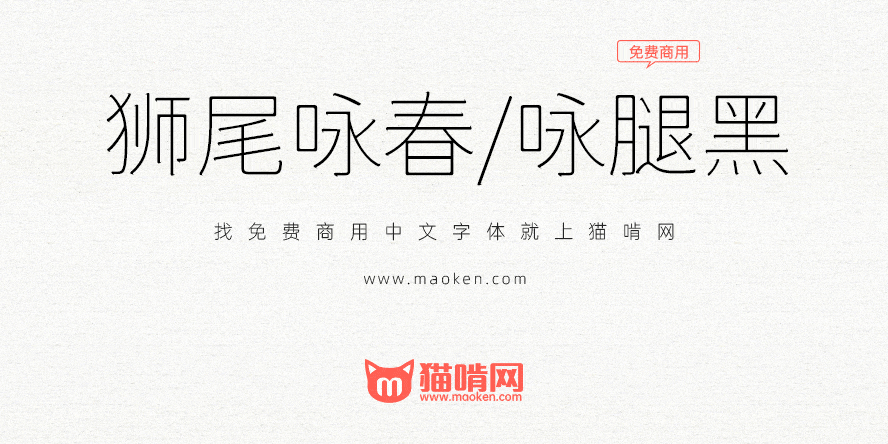
狮尾咏春黑体基于思源黑体的笔触长角和拔脚改造,更加简明现代化的字体。支援简体中文、繁体中文、韩文与日文;可以免费商用,欢迎大家自由应用、自由优化、自由改作!
狮尾咏春黑体的特色是:笔触长角,起头与收尾有利落感。
「狮尾咏春黑体」与「狮尾咏腿黑体」差别在有没有拔脚,「拔脚」就是会有较少的笔画,例如移除「口」字的左右下角会多出的短线条。有拔脚的字会较圆,但是会造成有些字因直接去掉腿后左右不平衡、左右不对衬的「悬空」问题。改使用「腿」系列字体就不会有这个问题。
应该是用FontForge软件的,Max有放出修改字体的脚本的~
是的,笔触可以加大加明显好些,但MAX好像有强迫症,每款字体都做7个字重,和拔脚不拔脚2种类型。这种特殊字体做1-3个字体足够用了,拔脚和不拔脚可以根据自己审美选一种就可以了。